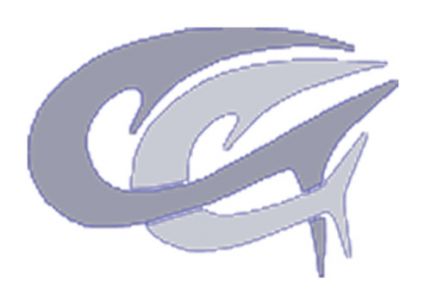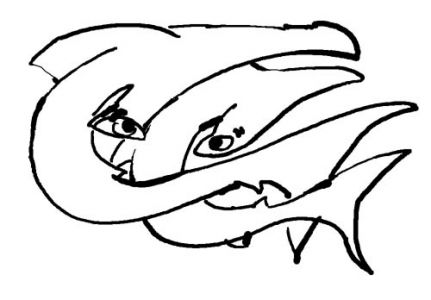
Langweilige Überschrift, aber was ist das für eine Schrift!
weiß jemand von euch was das für eine Schrift ist!
n euch was das für eine schrift ist!
achso, ich hatte noch vergessen:
blöd siehts auch aus :twisted:
Was stört dich daran!
Oder anders gefragt was sollte anders sein?
Springende Delfine sind nicht schlecht, für jemanden der gerne schwimmt und taucht, oder?
Hammerhaipäärchen, ganz klar :D
Springende Delfine snd das ganz bestimmt nicht. Ich hatte ja beim ersten Anschauen eine Assoziation, die in Richtung Liebesspiel ging, aber das Hammerhai-Pärchen ist unübertrefflich!
Ja das geht in die Richtung die mir gefällt.
Toll, das ist der Vorteil von dem Forum, man kann die Erfahrung vieler nutzen.
ähm. ok – versuchen wir noch was zu retten.
ich empfehle eine monogram mit einem c aus der delphin:
Es ging mir nur um Anregungen und die habe ich bekommen.
Nun gut über Geschmack kann man nicht streiten.